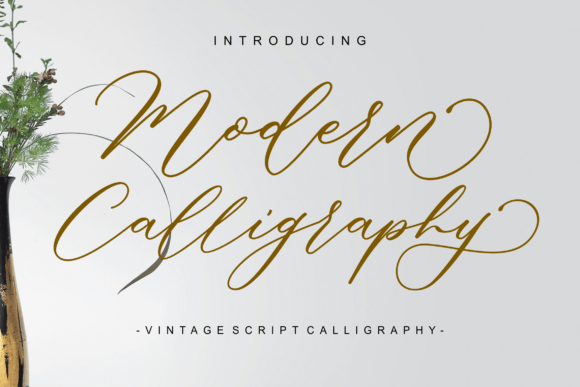
Modern Calligraphy
Modern Calligraphy – Une police vintage qui sublime vos créations
Modern Calligraphy est une typeface intemporelle qui capture toute l’élégance et le charme de l’écriture manuscrite d’antan. Ses traits fluides et ses courbes raffinées rappellent les calligraphies vintage, offrant un swash élégant et une sophistication instantanée à chaque projet.
Que vous travailliez sur un logo, des faire‑part de mariage, une identité de marque, une signalétique, ou encore le design d’un emballage, Modern Calligraphy apporte une touche d’authenticité et de luxe. Sa palette de traits détaillés et de boucles gracieuses crée un effet « script vintage » qui séduit immédiatement le regard.
Pourquoi choisir Modern Calligraphy ?
- Esthétique vintage – Rappel des manuscrits du XIXᵉ siècle avec des traits modernes.
- Polyvalence – Idéale pour les logos, invitations, branding, signalétique, affichage produit et packaging.
- Impact émotionnel – Évoque le romantisme, le luxe et la tradition en quelques caractères.
- Lisibilité soignée – Les courbes sont étudiées pour garder une lecture claire même en petite taille.
Applications concrètes
Logos & branding : donnez à votre marque une identité unique et mémorable.
Faire‑part de mariage : créez des invitations qui respirent la romance et l’élégance.
Signalétique & packaging : démarquez vos produits sur les étagères grâce à une typographie qui capte le regard.